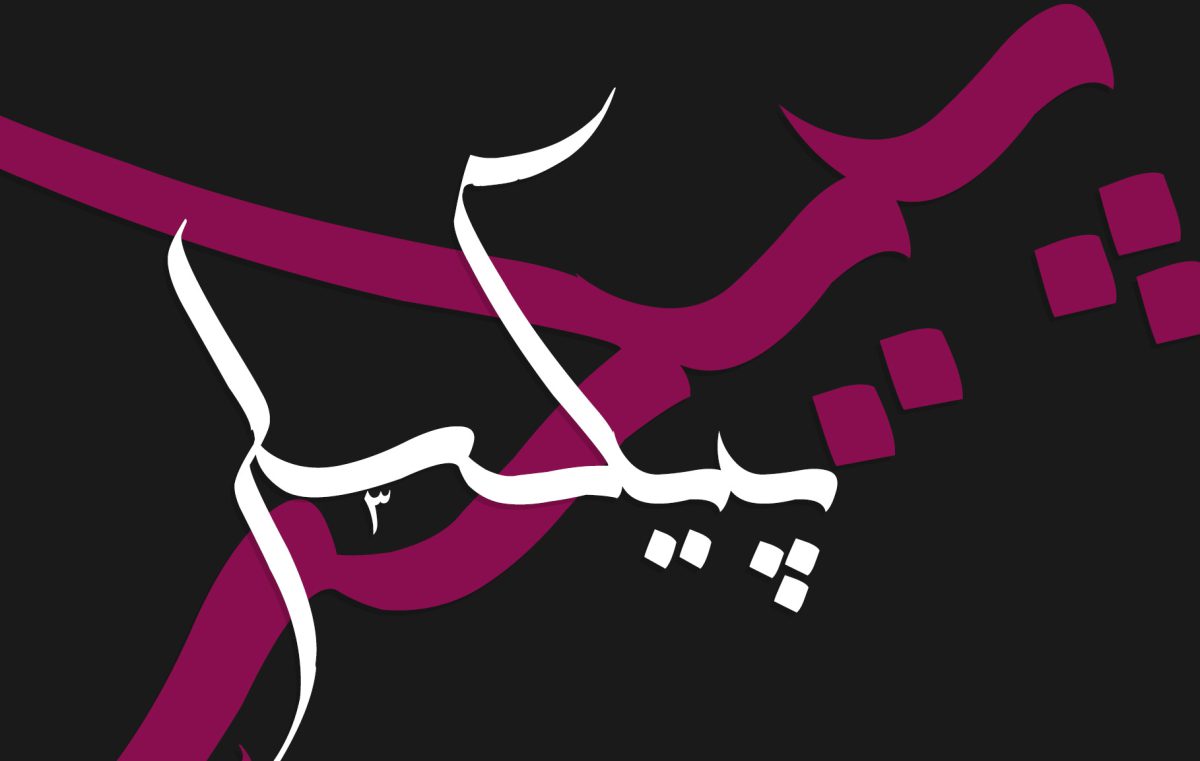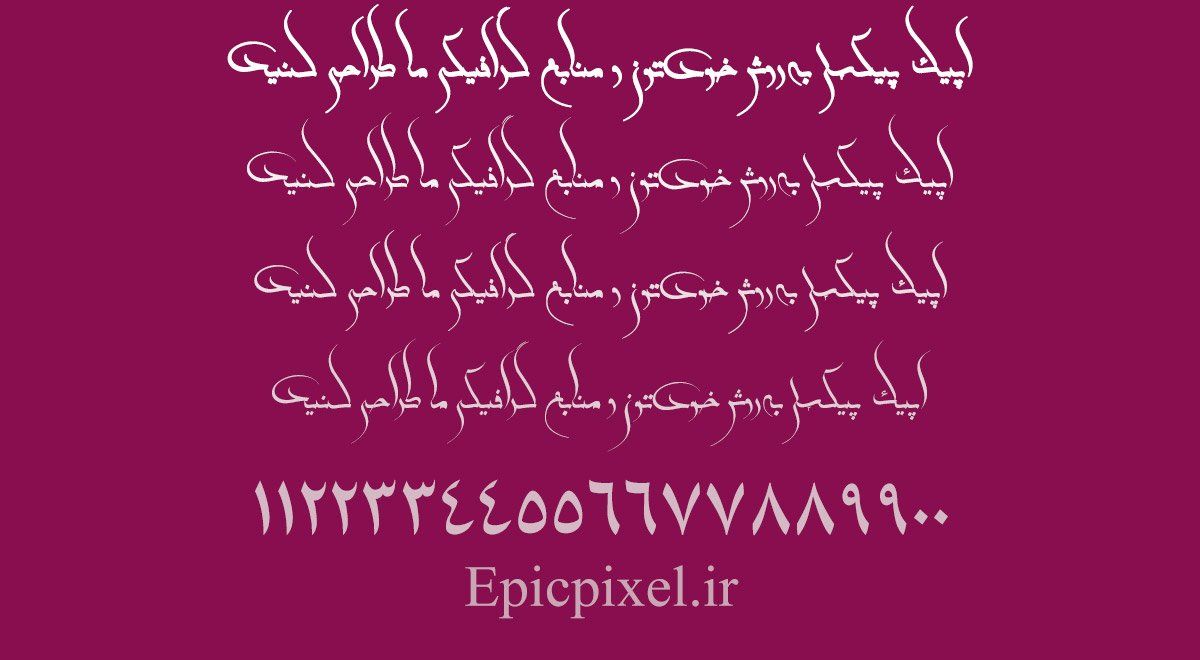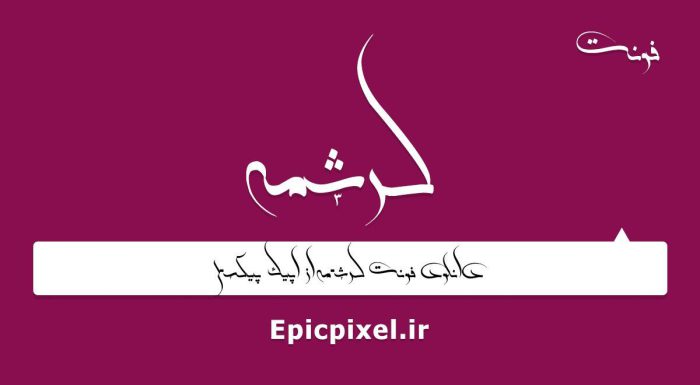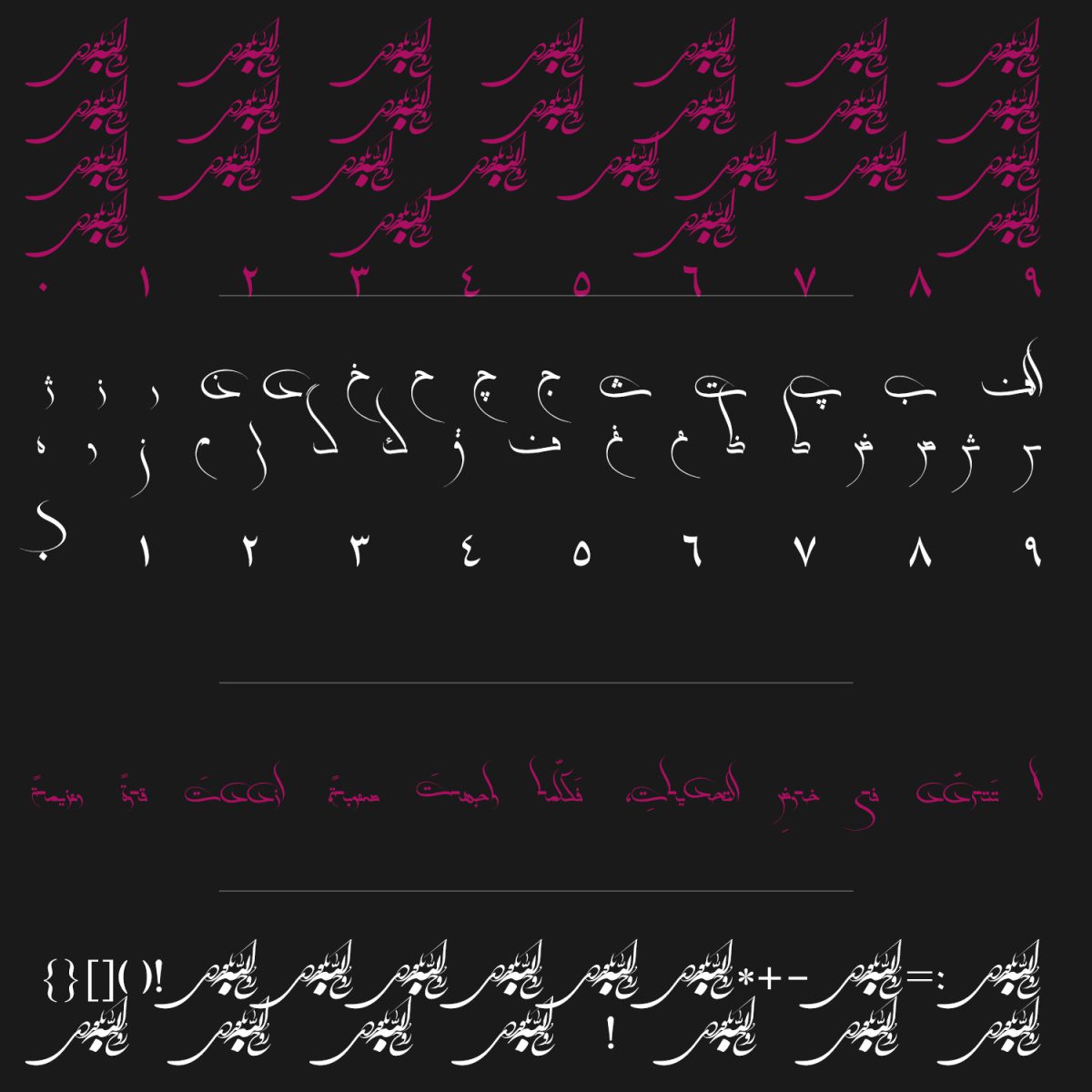
3 فونت کرشمه فارسی Kereshmeh
دانلود رایگان فونت کرشمه، قلمی زیبا و جدید بر اساس خط کرشمه است که توسط استاد احمد آریا منش بنیانگذاری شده و توسط آقای امیر حسین صدقی به فونت تبدیل گشته. این فونت با سبک منحصر به فرد و ظرافت های خاص در پیچش ها، در سه نسخه (A Kereshmeh, Dima Kereshmeh, Persian Kereshmeh) با یک استایل کلی ارائه می شود. کرشمه با فرمت TTF، برای انواع طراحی ها، به خصوص مذهبی، پوستر، بنر و لوگوتایپ مناسب است و نسخه پرشین کرشمه آن به صورت رایگان قابل دانلود می باشد. این قلم زیبا دارای حروف و اعداد فارسی بوده و در نرم افزارهای ویندوز و موبایل قابل استفاده است و با جذب مخاطب، تایپوگرافی چشم نوازی خلق می کند. این فونت میتونه از زیر مجموعه های فونت نستعلیق هم باشه
مشاهده و دانلودفونت فارسی کرشمه: قلمی جدید با سبک خطاطی استاد احمد آریا منش برای طراحی
فونت فارسی کرشمه، نمونه ای دیجیتالی از خط کرشمه است که توسط استاد احمد آریا منش بنیانگذار این خط بکر و جدید فارسی، ابداع و توسعه یافته است. زیبایی و شیرینی زبان فارسی با خطوط مختلف خوشنویسی افزایش می یابد و خط کرشمه با سبک نوآورانه خود، به این زیبایی افزوده است. این خط با الهام گیری از منابع مختلف، از جمله خط میخی در گنج نامه همدان، به شکلی پر پیچ و خم و با ظرافت های خاص در پیچش ها و اتصال حروف به هم شکل گرفته که سماع آدمی را به خاطر می آورد و نام “کرشمه” (با مفهومی نزدیک به ناز و جلوه) با آن هماهنگی دارد و تأیید دیگران را نیز به همراه داشته است. استاد آریا منش تاریخچه این خط و فرآیند تکامل آن را شرح داده و آثار و یافته های خود را در کتابی در سال ۱۳۷۹ گرد آورده اند. این خط هنوز جوان است و در مسیر پختگی و تکامل قرار دارد و نیاز به سالیان دراز کار مداوم دارد.
دانلودفرآیند تبدیل خط کرشمه به فونت کامپیوتری برای اولین بار توسط آقای امیر حسین صدقی انجام شده است، با شروعی حدود نوروز ۹۸ شمسی. این تلاش ها به اهمیت تبدیل دستخط های زیبای فارسی به فونت های کامپیوتری پاسخ می دهد که با فراگیر شدن تایپ دیجیتال، اهمیت دوچندانی یافته است و امکان استفاده از خطوط سنتی در دنیای مدرن را فراهم می کند.
مجموعه فونت های کرشمه شامل 3 فونت کرشمه به نام های A Kereshmeh , Dima Kereshmeh , Persian Kereshmeh است. این ها 3 فونت با یک سبک استایل اصلی و با اسامی مختلف برای تکمیل این ارشیو و ارائه انتخاب های متنوع تر به طراحان هستند ( سری فونت A و پرشین کاملا شبیه به هم هستند ولی سری فونت دیما متفاوت ) تا بتوانند از این سبک در قالب های مختلف بهره ببرند. همچنین اشاره شده که فونت دیما کرشمه یکی از فونت های خانواده کرشمه است که طراحی جذاب و نزدیک به طراحی عربی دارد و در کنار فونت هایی نظیر کاردونا، هاجر و ثلث قرار می گیرد، اما ریشه آن در یک خط فارسی جدید است.
فونت کرشمه فونتی زیبا است که شکل و شمایلش با اسمش هماهنگی دارد. این فونت با فرمت TTF ارائه می شود که پرکاربردترین فرمت فونت برای استفاده در نرم افزارهای مختلف است و در اکثر نرم افزارهای گرافیکی قابل استفاده میباشد. همچنین قابل نصب روی موبایل و تمام برنامه هایی که قابلیت تایپ و نصب فونت در آنها فراهم است. کرشمه دارای کیفیت بالای طراحی فونت است و شامل تمامی حروف فارسی و دارای اعداد فارسی می باشد که آن را برای استفاده در متون فارسی کامل و کاربردی می سازد.
فونت کرشمه برای انواع طراحی ها مناسب است. به خصوص در طراحی های مذهبی، پوسترها و بنرهای تبلیغاتی و… می توان از آن بهره گرفت. همچنین می توان با اعمال تغییراتی، لوگوتایپ جذابی را نیز توسط این فونت خلق کرد. انعطاف پذیری محتوایی و فرمی فونت که قابلیت استفاده آن در تیترنویسی و نیز در کارهای گرافیکی را با جذب مخاطب به خود امکان پذیر می کند، این قلم را از هم ردیف های تزیینی خود متمایز و آن را به عنوان تایپوگرافی چشم نوازی معرفی می کند. این فونت میل به نمایش ایده پردازی هایی که چشم و فکر را از گونه های متداول و گاه کلیشه ای تایپوگرافی فاصله می دهد، برآورده می کند.
کاربردهای فونت کرشمه در طراحی گرافیک
با توجه به سبک هنری، ظرافت های خاص، و انعطاف پذیری، فونت کرشمه کاربردهای گسترده ای در طراحی گرافیک دارد و برای خلق آثاری با جلوه ای هنری، اصیل و چشم نواز مناسب است. این قلم زیبا برای انواع طراحی ها مناسب است، به خصوص در طراحی های مذهبی، پوسترها، بنرهای تبلیغاتی و… می توان از آن بهره گرفت. همچنین برای خلق لوگوتایپ جذابی (با اعمال تغییرات)، تیترنویسی و کارهای گرافیکی با جذب مخاطب بسیار مؤثر است. این فونت مناسب برای انواع طراحی ها، تایپوگرافی و نوشتن متون خاص می باشد و به عنوان تایپوگرافی چشم نوازی معرفی شده است. قابل نصب روی موبایل و تمام برنامه هایی که قابلیت تایپ و نصب فونت در آنها فراهم است، امکان استفاده از آن را در پروژه های مختلف فراهم می کند. همچنین می تواند به عنوان جایگزینی دیجیتالی برای نگارش نامه با دستخط های زیبا استفاده شود.